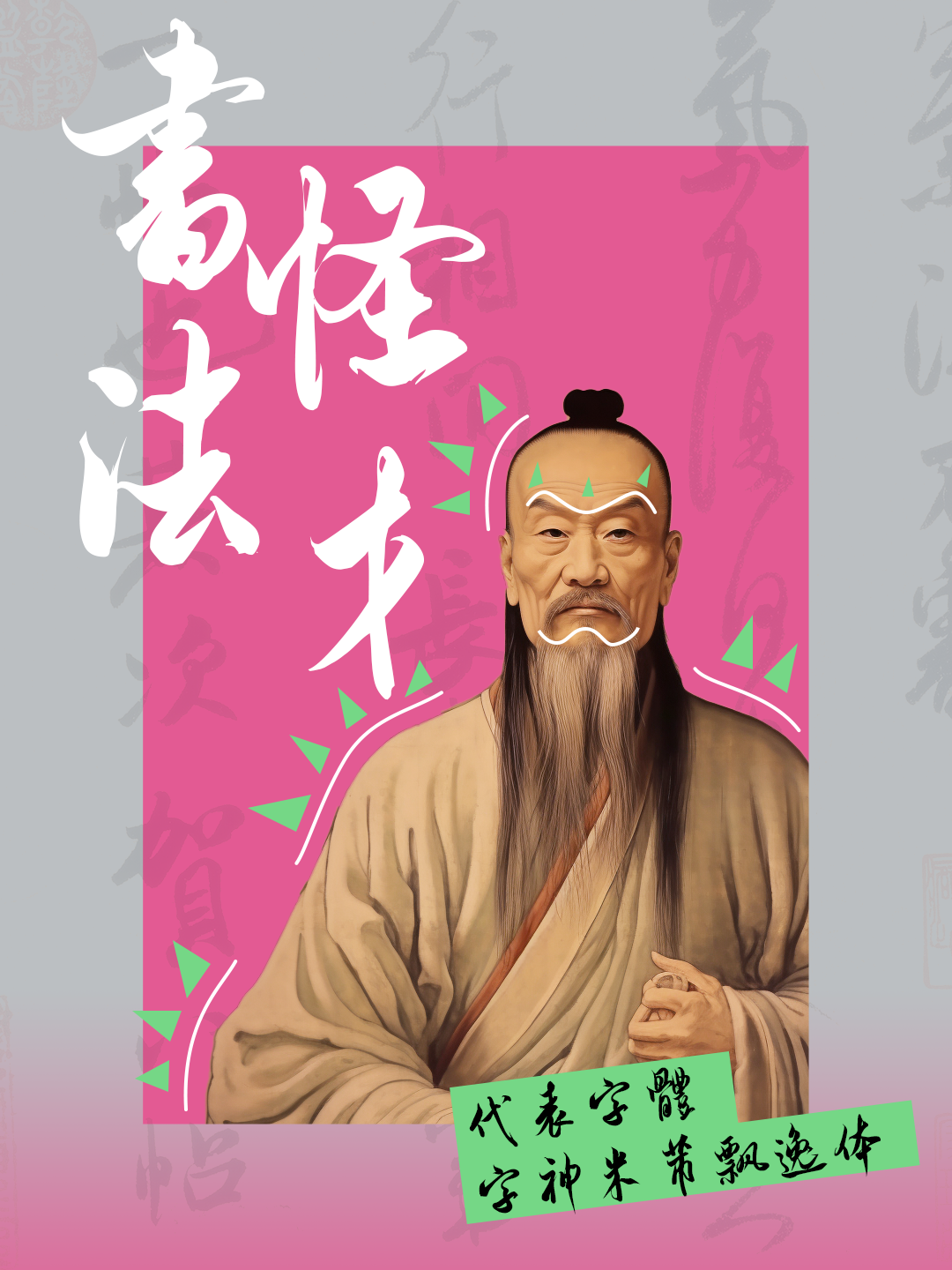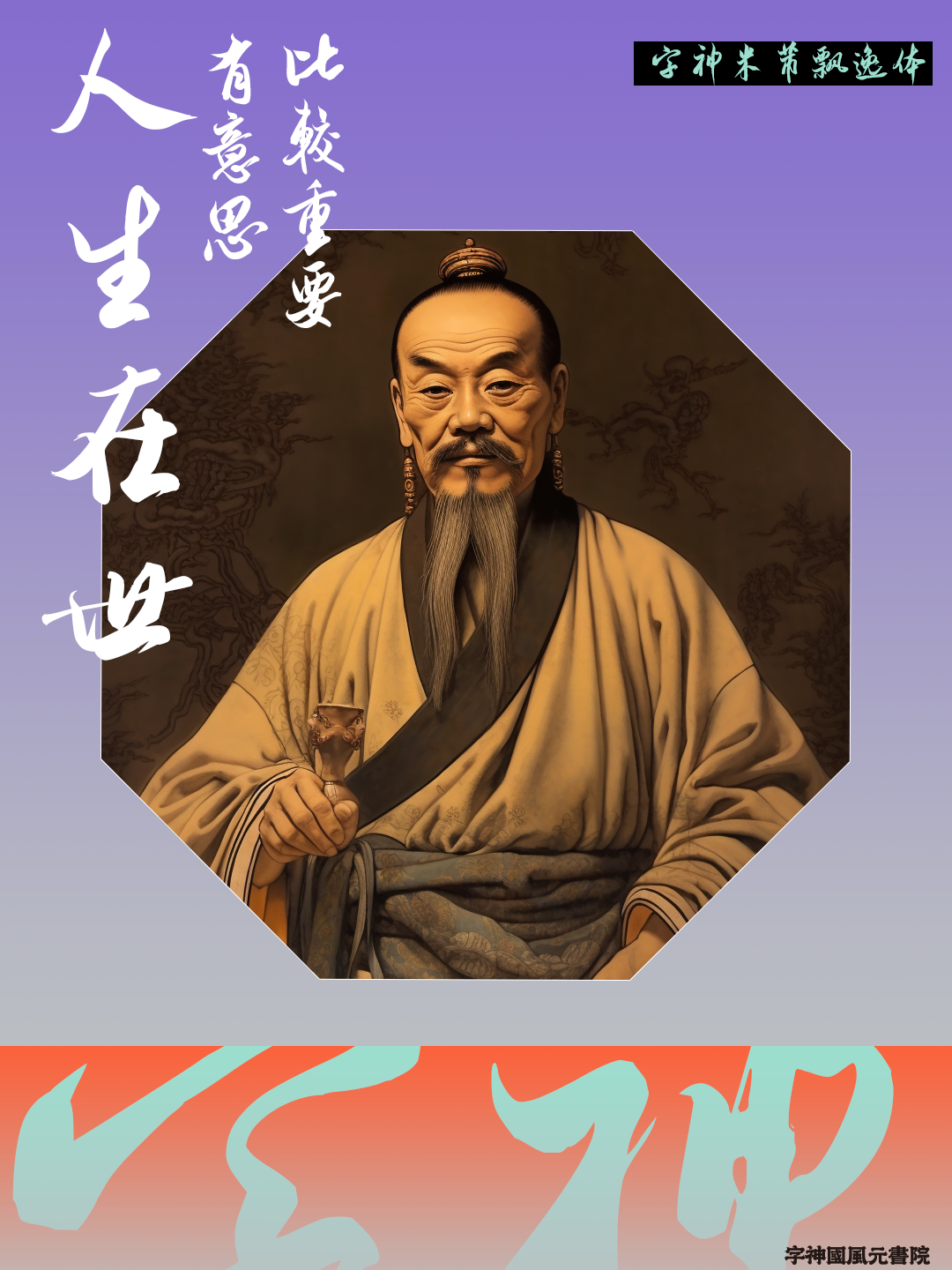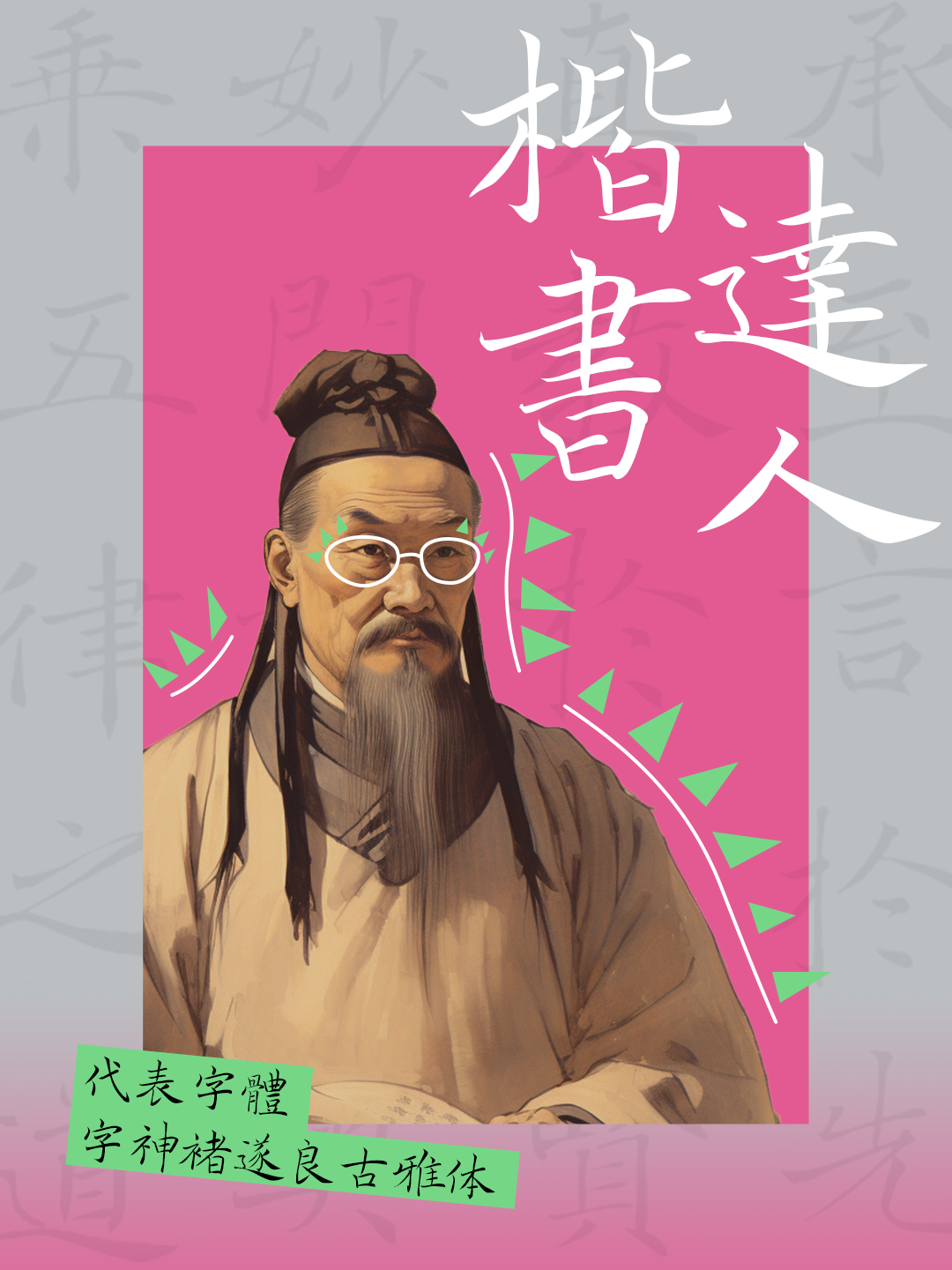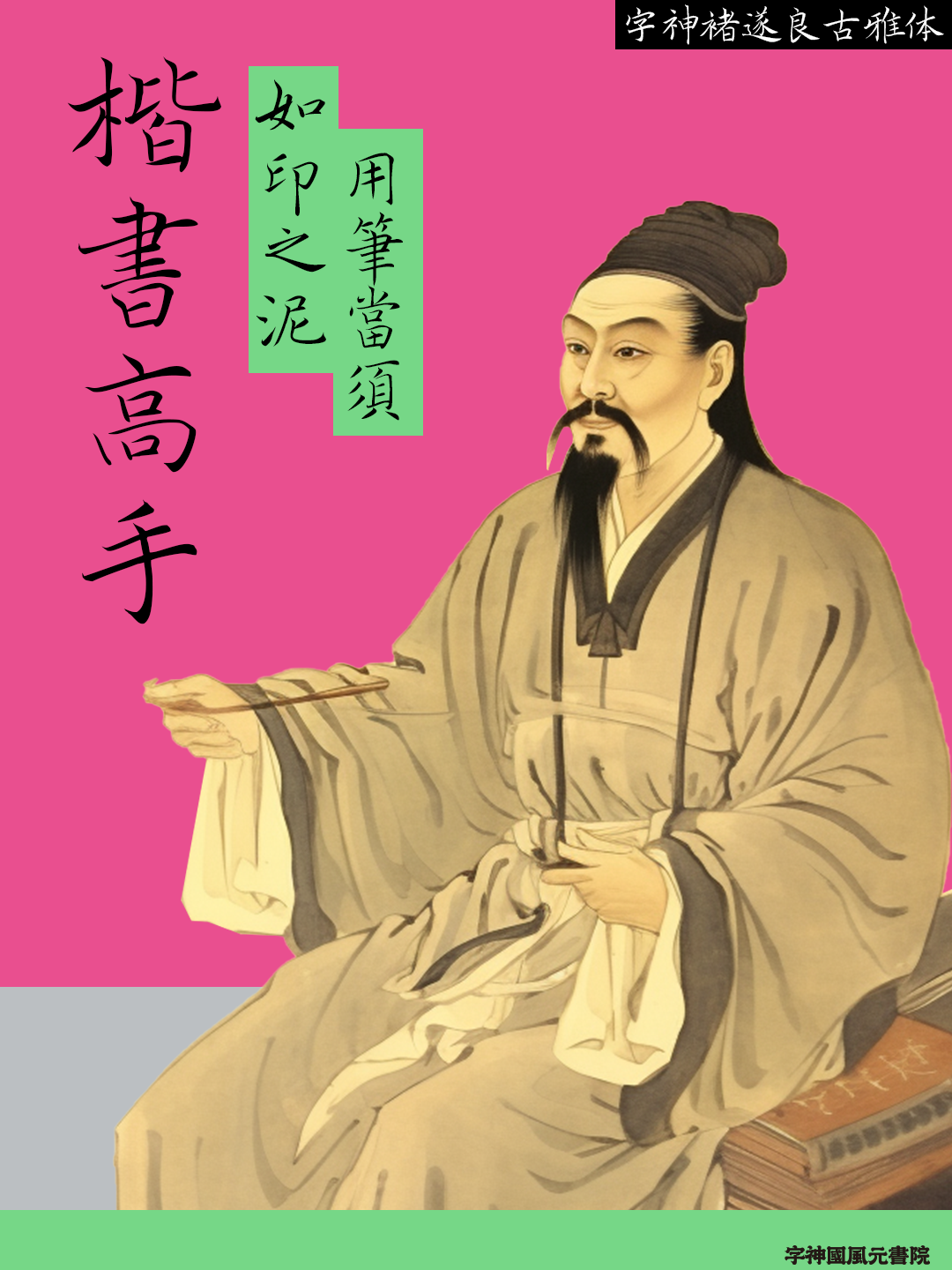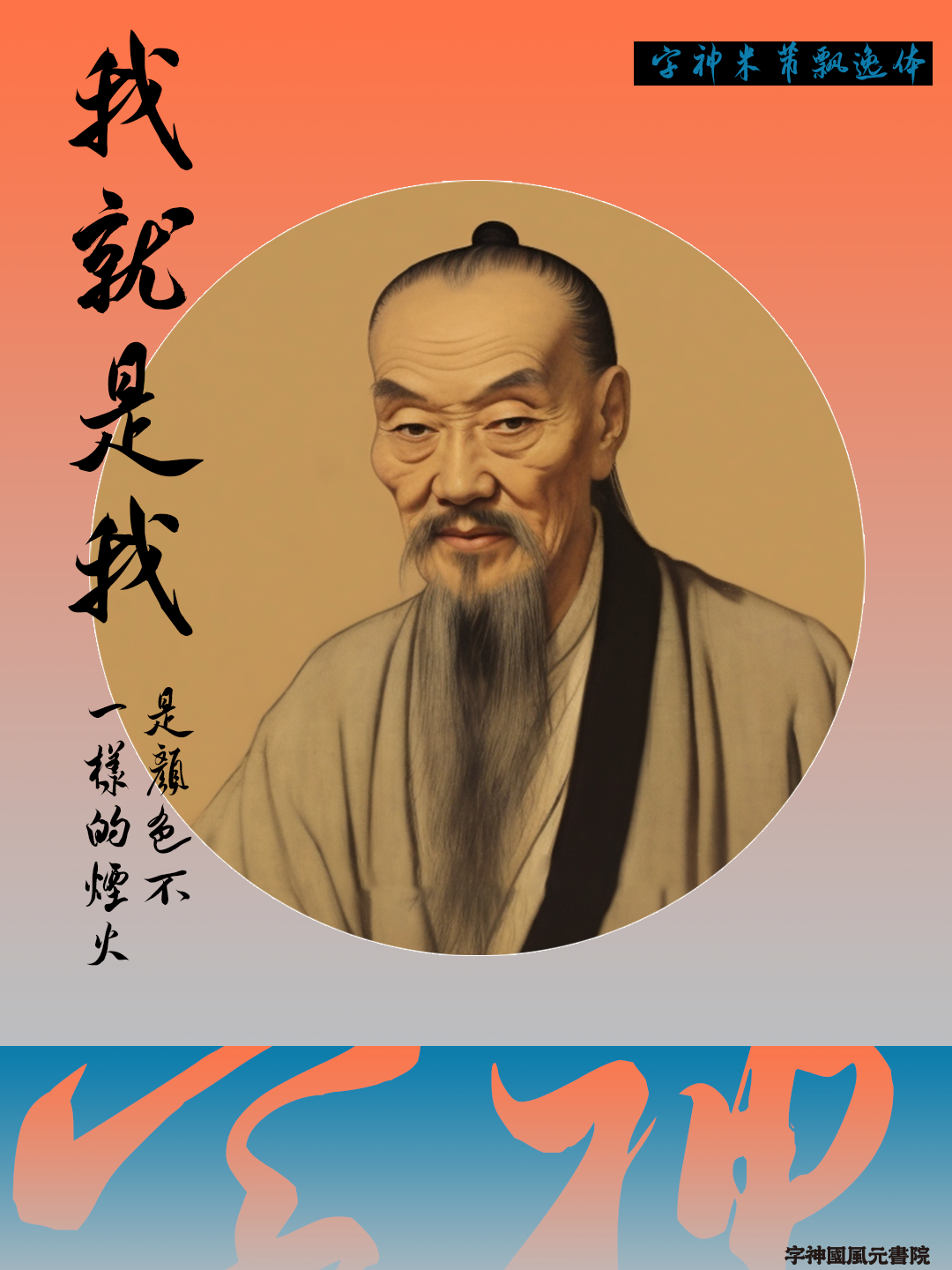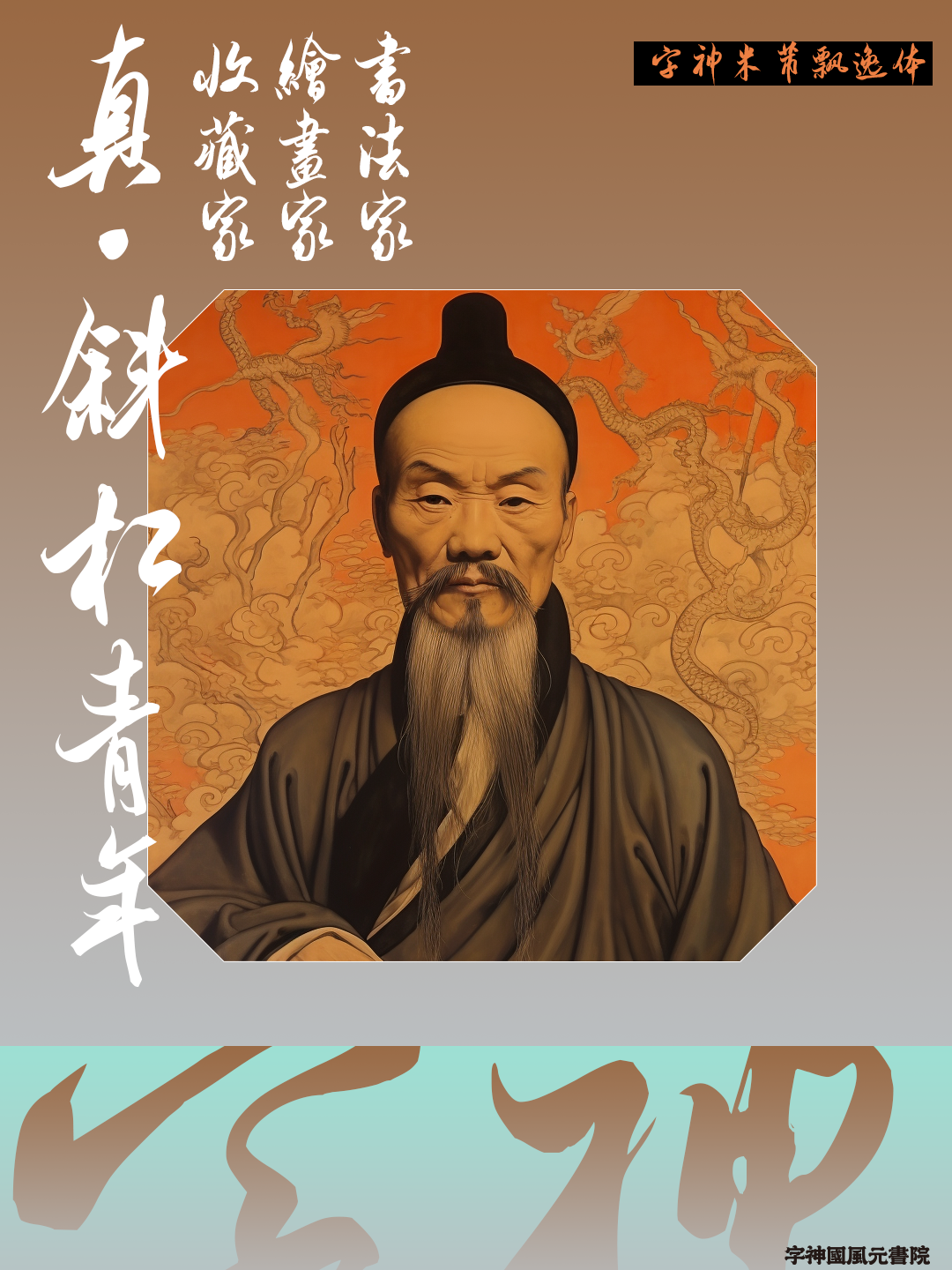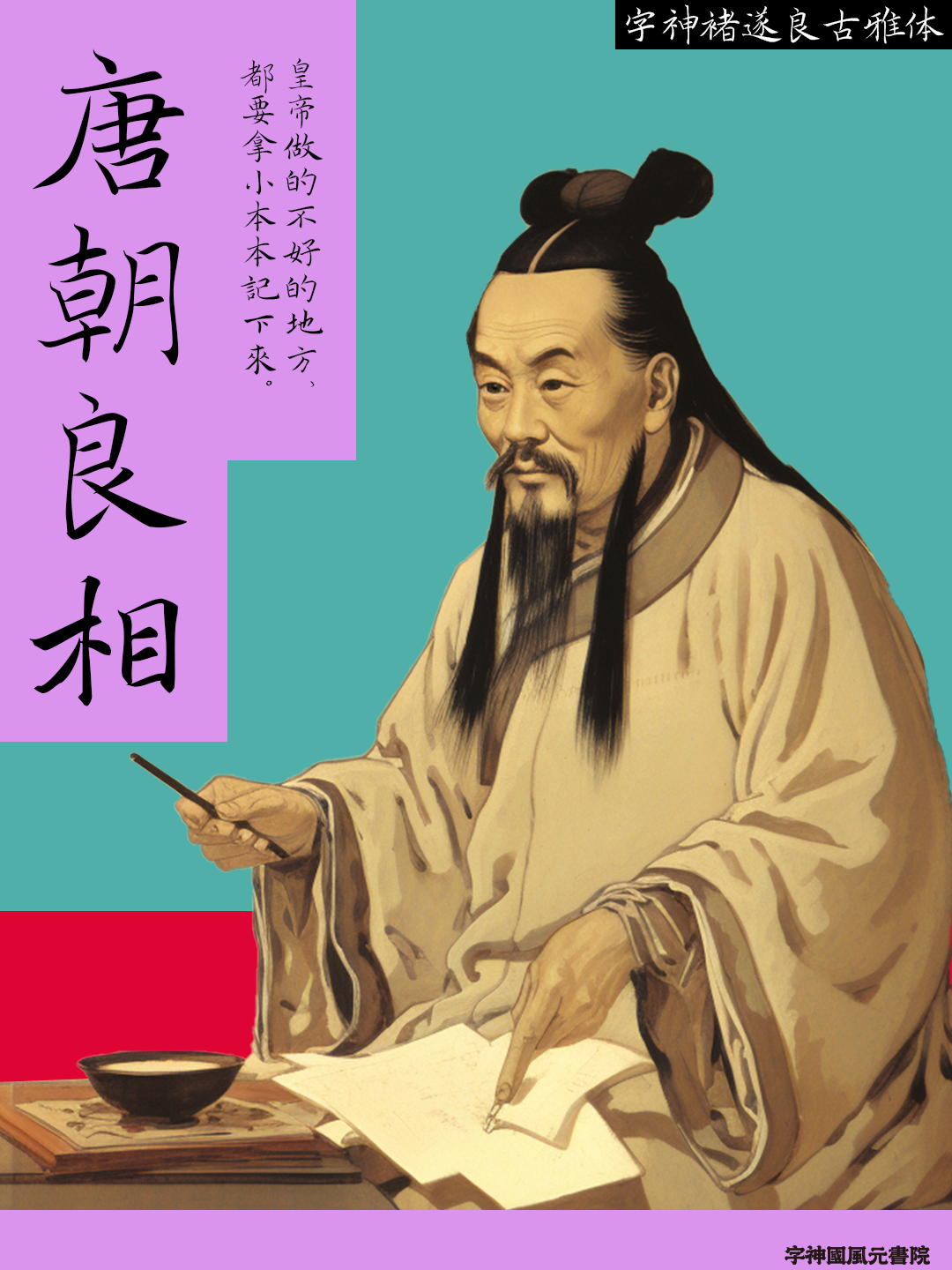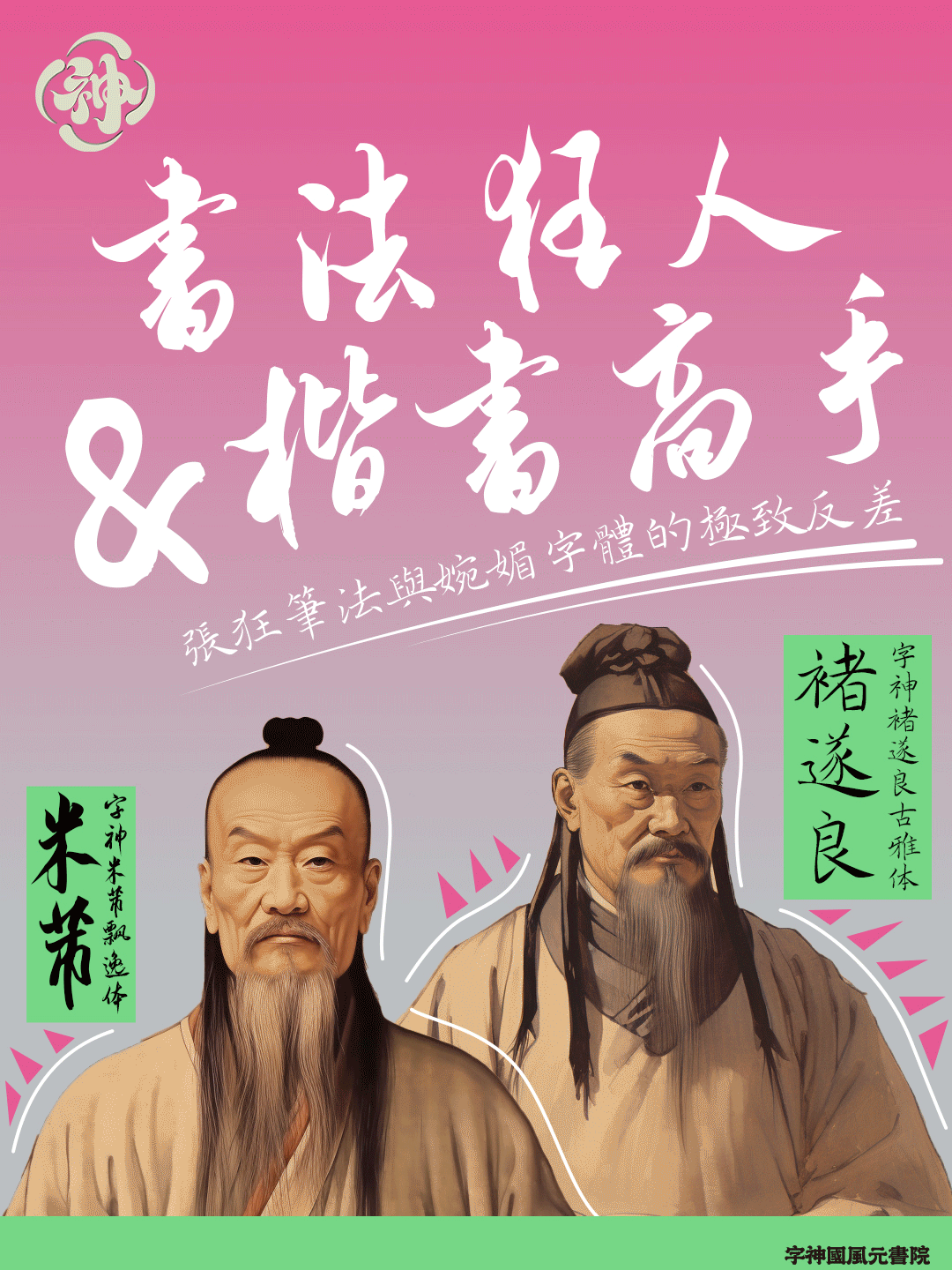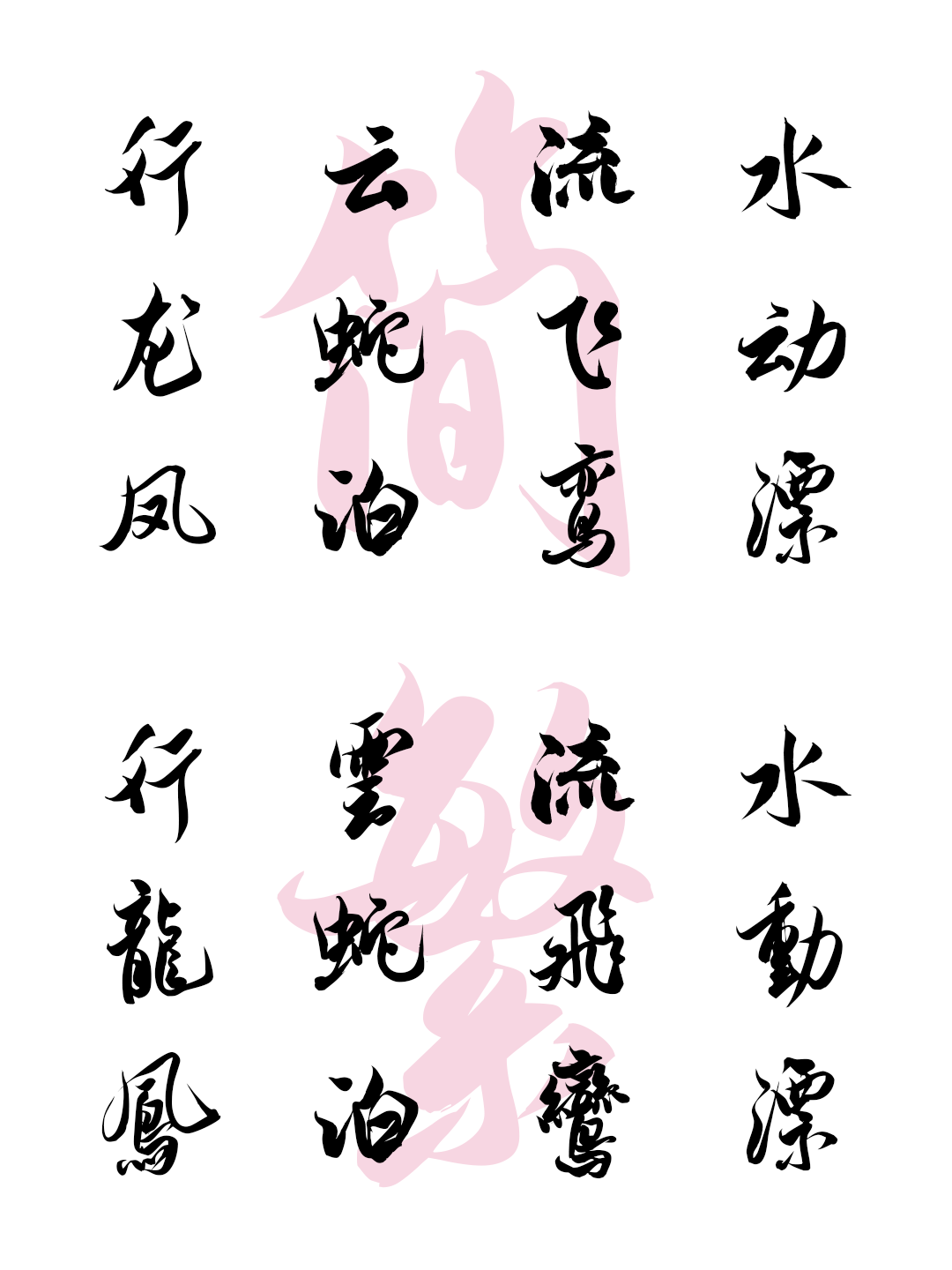
字神新字|AI字神图鉴——米芾&褚遂良,张狂笔法与婉媚字体的极致反差!
今天我们邀请两位历史上的书法名人——米芾&褚遂良,用AIGC技术让字神穿越时空,同时以字体链接古代艺术,与之进行对话,再现字神精妙笔法,欣赏其作品中表达的艺术追求与审美观念。
Part 1.米芾
要说最疯的书法家之一,米芾必须榜上有名,而他的「疯」,是对于书法的热爱与痴狂,是沉迷于自我世界的与情趣,是无惧世俗之见的率性与不羁。那么被称为「米癫」的他,是如何破茧而出,疯出文采、疯出情怀的?
代表作品
我们可以从米芾的书法中窥见他的内心世界。字神米芾飘逸体,体现出他性格中的颠与狂,笔画中可以看出他深厚的用笔功力。
整体呈现出刚柔并济、飘逸秀丽之感,用笔灵动飘逸、沉着多变,结体取势险绝,寻求奇趣的同时却不失平稳。
善于利用参差错落、空间疏密与笔画轻重对比等造就独特风貌。在变化中达到统一,把裹与露、肥与瘦、疏与密、简与繁等对立因素有机融合起来。
笔墨流转之间,自由而洒脱的人生态度跃然纸上。
Part 2.褚遂良
那么接下来我们介绍一下米芾最仰慕的人——褚遂良。
与米芾的张狂笔法不同,褚遂良的书法艺术则凝聚了他的从佛教中汲取人生智慧,不呆板,非常灵动,别有趣味。
代表作品
字神褚遂良古雅体,在运笔上则采用方圆兼施,逆起逆止;横画竖入,竖画横起,首尾之间皆有起伏顿挫,提按使转以及回锋出锋都有一定的规矩。
用笔纤细空灵,精妙无比。婉媚遒劲,波拂处蜿蜒如铁线。弧线的大量使用,使原本笔直、坚挺的基本笔画,增加了柔和委婉、妩媚灵动,再加上起笔处的回笔扭动,婀娜多姿,颇有韵味。
因地制宜、布局舒朗、字势灵动,擅长制造险峻,同时又能够轻松破除,简繁转换更具古雅气息。
正如楷书端正的特点一般,褚遂良不仅学识渊博,性格也极为耿直,敢于坚持原则。
字神米芾飘逸体&字神褚遂良古雅体
类型:行书&楷书
风格气质:国风、新中式